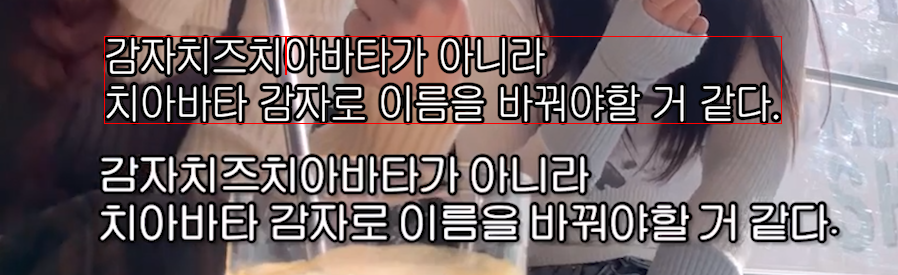
굴림체 같은데 뭘까요? cha*** 2024.05.06 조선굴림체는 해보니까 더 길쭉한 느낌이 강하더라고요 감자치즈 어쩌고는 위가 조선굴림체 밑에가 제가 찾고있는 폰트입니다! 댓글 0 등록 쉽고 빠르게 가장 비슷한 폰트를 알고 싶다면? 이미지로 검색하기
감자치즈 어쩌고는
위가 조선굴림체
밑에가 제가 찾고있는 폰트입니다!